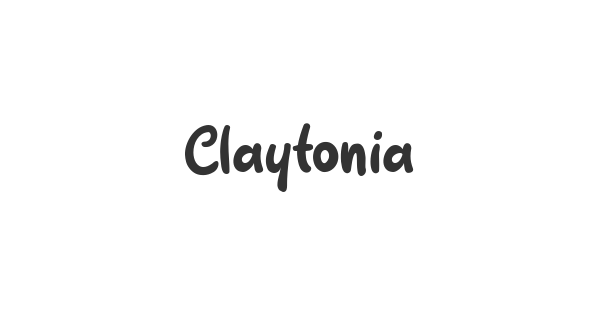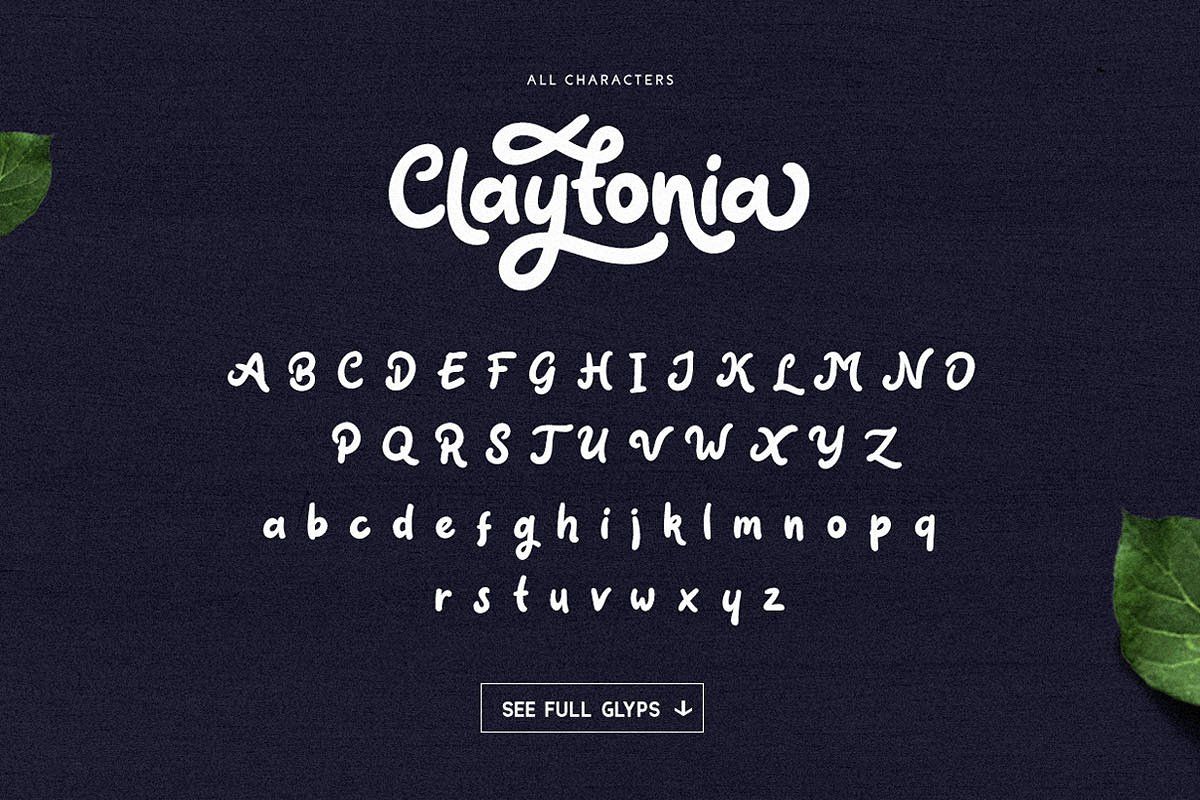
Font SVN-Claytonia là gì?
SVN-Claytonia là một phông chữ Script mang phong cách cổ điển đặc trưng của những năm 70. Với các nét chữ tròn trịa, dày dặn và uốn lượn mềm mại, Claytonia gợi lên cảm giác hoài cổ, ấm áp nhưng vẫn đầy sự sang trọng. Đây là lựa chọn xứng đáng cho thiết kế logo ngành cafe, tiệm bánh, thời trang thủ công hoặc các mẫu hộp đựng mang tính hoài niệm.
Tuy nhiên, phông chữ này có cấu trúc nét nối rất phức tạp. Nếu sử dụng các bản tải font SVN-Claytonia không chuẩn, khi thực hiện in ấn trên các chất liệu thấm mực như túi giấy Kraft, các nét nối này rất dễ bị nhòe dính vào nhau. Bản việt hóa tại In Viva đã được tinh chỉnh độ hở giữa các nét, đảm bảo chữ hiển thị rõ ràng ngay cả khi in kích thước nhỏ trên tem nhãn mỹ phẩm.
Ứng dụng font SVN-Claytonia việt hóa trong thiết kế và sản xuất
Phong cách Vintage của Claytonia giúp nâng tầm giá trị thẩm mỹ cho các ấn phẩm:
- Thiết kế logo và bao bì ngành thực phẩm sạch: Những nét chữ uốn lượn in trên hũ mật ong, hộp trà hay túi cafe tạo cảm giác tin cậy về nguồn gốc tự nhiên và truyền thống lâu đời.
- Sản xuất hộp đựng đặc sản: Claytonia rất phù hợp để in tiêu đề trên các hộp cứng đựng bánh Trung thu hay hộp quà Tết mang màu sắc dân gian.
- Khắc laser tinh xảo lên bút ký và sổ tay gỗ: Các đường nét uốn lượn của Claytonia được In Viva xử lý khắc sâu, tạo độ tương phản sang trọng trên bề mặt gỗ cao cấp.
- Trang trí thiệp mời sự kiện khai trương: Tạo sự khác biệt và ấn tượng mạnh mẽ cho khách mời thông qua những tà chữ cổ điển sắc sảo trên giấy mỹ thuật.